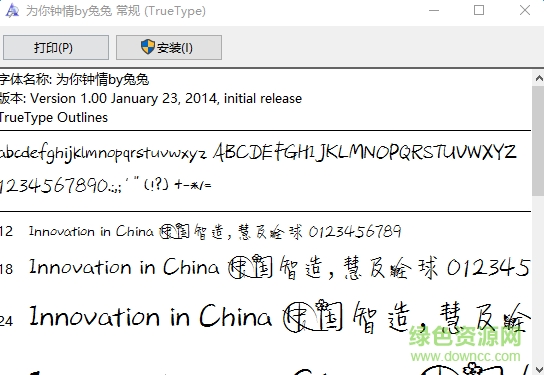
為你鐘情字體是一款很有特色的電腦藝術(shù)字體,這款字體寫(xiě)出來(lái)的字是非常好看的,活潑、大方,具有自己獨(dú)特的魅力,喜歡的這款字體的朋友可以來(lái)綠色資源網(wǎng)下載。
為你鐘情字體是一款很不錯(cuò)的的藝術(shù)字體,充滿了藝術(shù)的味道,用于藝術(shù)設(shè)計(jì)是再合適不過(guò)了,歡迎大家來(lái)綠色資源網(wǎng)下載。